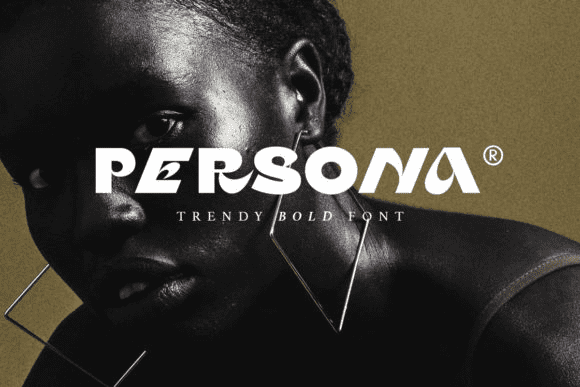
Название: Persona Font
Persona - это жирный и модный шрифт для дисплея.
Независимо от темы, этот шрифт будет невероятно полезным для библиотеки ваших шрифтов, так как он способен возвысить любое творение.